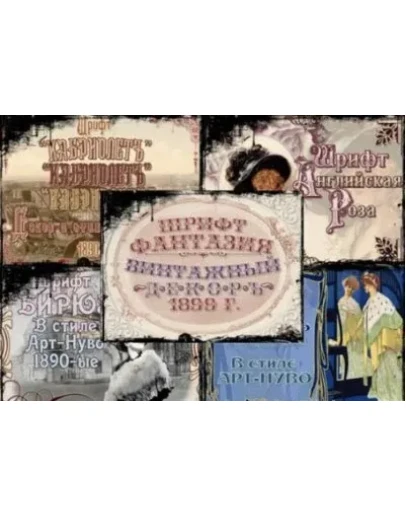
• Винтажные шрифты 1918 года + БОНУС
Шрифты отрисованы из книги "Каталог словолитень 1918 года"
ВНИМАНИЕ! Шрифты БЕЗ ЛАТИНИЦЫ, в некоторых нет цифр (т.к. отрисовывалось с книги).
Elzevir - Эльзевир (знаки препинания есть, цифр нет),
Old Classic - Старая Классика (знаки препинания и цифры есть),
Pompadur - Помпадур (знаки препинания и цифры есть),
Redinger - Редингер (знаки препинания и цифры есть),
Romana Script - Романа скрипт (знаки препинания и цифры есть),
Round Script - Круглорукописный (знаки препинания и цифры есть),
Script Thin pen - Скрипт Тонкое перо (знаки препинания и цифры есть),
Venecia - Венеция (знаки препинания некоторые есть, цифр нет),
Roland-Decor - Роланд Декор (знаки препинания и цифры есть),
Tchekhonin1 - Буквицы (рисунки в древнерусском стиле) Чехонин1 (только буквицы),
Tchekhonin2 - Буквицы (рисунки в каллиграфическом стиле) Чехонин2 (только буквицы),
Zaglavny - Заглавный (знаки препинания некоторые есть, цифр нет).
Винтажные русские шрифты Часть 2 (количество - 8 штук).
В этих шрифтах присутствуют латинские символы, цифровая часть, знаки препинания и др. символы.
Kabriolet - (3 стиля) Кабриолет,
Birusa - Бирюза,
English Rose - Английская Роза,
Fantasia - Фантазия,
Flamingo - Фламинго,
Konrad-Modern - Конрад-Модерн.
Винтажные русские шрифты Часть 3 (количество - 15 штук)
Шрифтовое семейство "КантриВестерн" и "Оперина" + Фонт-Мест и P22